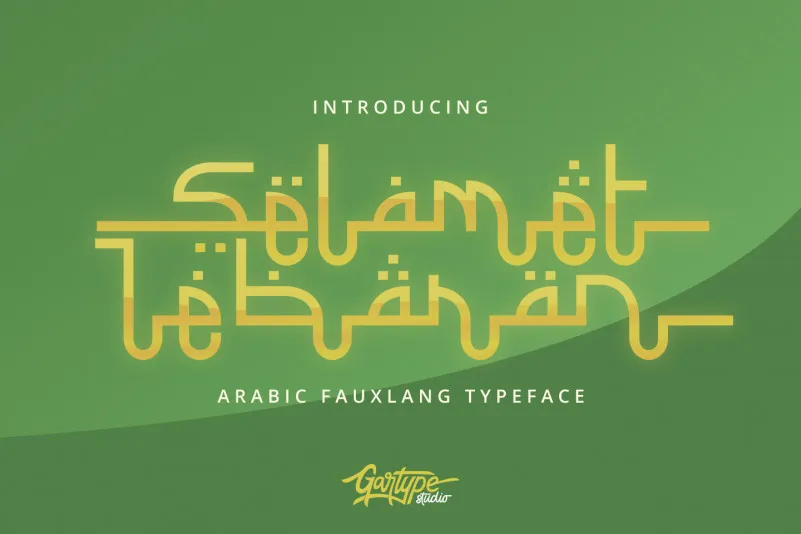
Selamet Lebaran é uma tipografia fictícia árabe criada pela Gartype Studio para os amantes do design que buscam algo único e inspirador. Inspirada nos traços arduamente perfeitos das letras árabes, essa fonte se destacaria especialmente em projetos como cartões de aniversário, posters de divulgação, headlines ambiciosas, ou mesmo a etiqueta personalizada para camisetas e produtos promocionais. Suavemente suave e rica em detalhes, Selamet Lebaran oferece uma experiência visual única que combina elegância com modernidade. Seu design sofisticado pode se adaptar facilmente a diversos tipos de projeto, tornando-se um recurso valioso para quem busca expressar sua identidade ou mensagem de forma distintiva e memorável. Com seu estilo único, Selamet Lebaran é perfeito tanto para aplicativos digitais quanto para impressão tradicional. É uma escolha ideal para aqueles que buscam fontes arábicas inspiradas no folclore e arte da escrita árabe, mas com um design moderno que transcende as barreiras culturais. Seja você designer gráfico ou criativo, Selamet Lebaran oferece uma maneira original de dar vida às suas ideias.
Designer: Gartype Studio